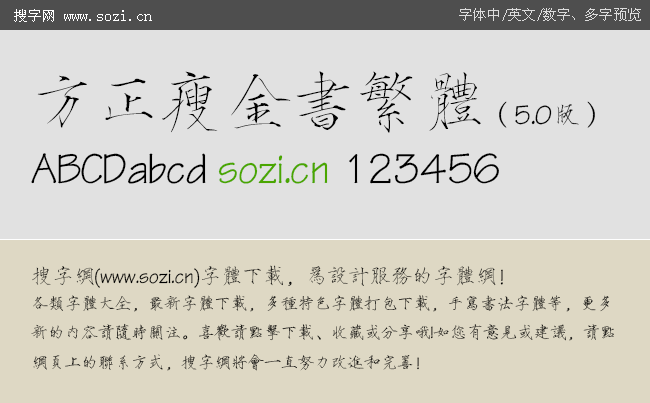
方正瘦金書繁體
搜字網(wǎng)提供一款書法字體方正瘦金書繁體字體下載,瘦金體為宋徽宗趙佶所創(chuàng),是書法史上的一項獨(dú)創(chuàng)。瘦金體運(yùn)筆飄忽快捷,筆跡瘦勁,至瘦而不失其肉,轉(zhuǎn)折處可明顯見到藏鋒,露鋒等運(yùn)轉(zhuǎn)提頓痕跡,是一種風(fēng)格相當(dāng)獨(dú)特的字體。適合字貼、招貼、書法畫冊設(shè)計應(yīng)用。